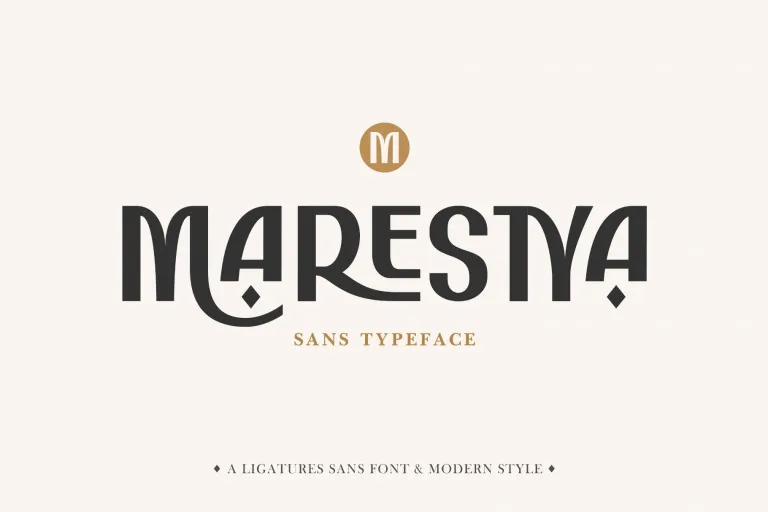
Marestya Font é uma elegante fonte sans serif desenvolvida pelo Silverdav Studio, com um toque moderno. Esta fonte oferece muitos alternativos e ligaturas que quando combinados criam designs atraentes, tornando seu trabalho ainda mais impactante e sofisticado. Com Marestya Font, você verá seus trabalhos se destacarem em qualquer plataforma digital ou impressa. Este é o complemento perfeito para designers atentos ao detalhe buscando criar um design que impressione. Teste sua versatilidade agora com a Marestya Font e observe como ela transforma suas ideias em arte.